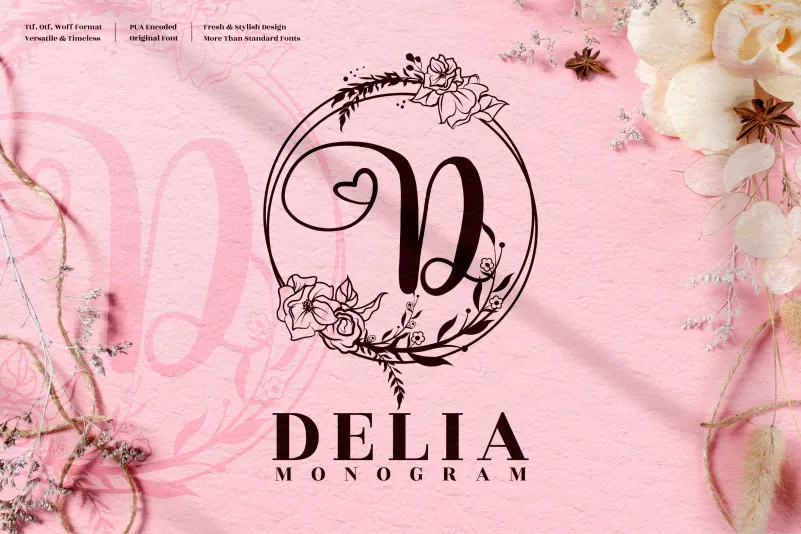
Delia Monogram Font
Esta é uma elegante fonte decorativa que apresenta ornamentos florais luxuosos. Perfeito para quem busca uma fonte sofisticada e única, a ‘Delia Monogram Font’ é perfeita para criar cartões de aniversário fofinhos, arte de papelaria incrível, postagens sociais memoráveis, criações lindas para selos e até mesmo invitations de casamento. A sua característica mais marcante são os ornamentos florais que adicionam um toque luxuoso a qualquer design. Este é o tipo de fonte que vai deixar seu projeto em evidência sem precisar de muito esforço, garantindo uma sensação autêntica e única. Seja para cartões personalizados ou selos elegantes, esta ‘Delia Monogram Font’ da perspectype certamente irá lhe ajudar a criar designs impecáveis e memoráveis.